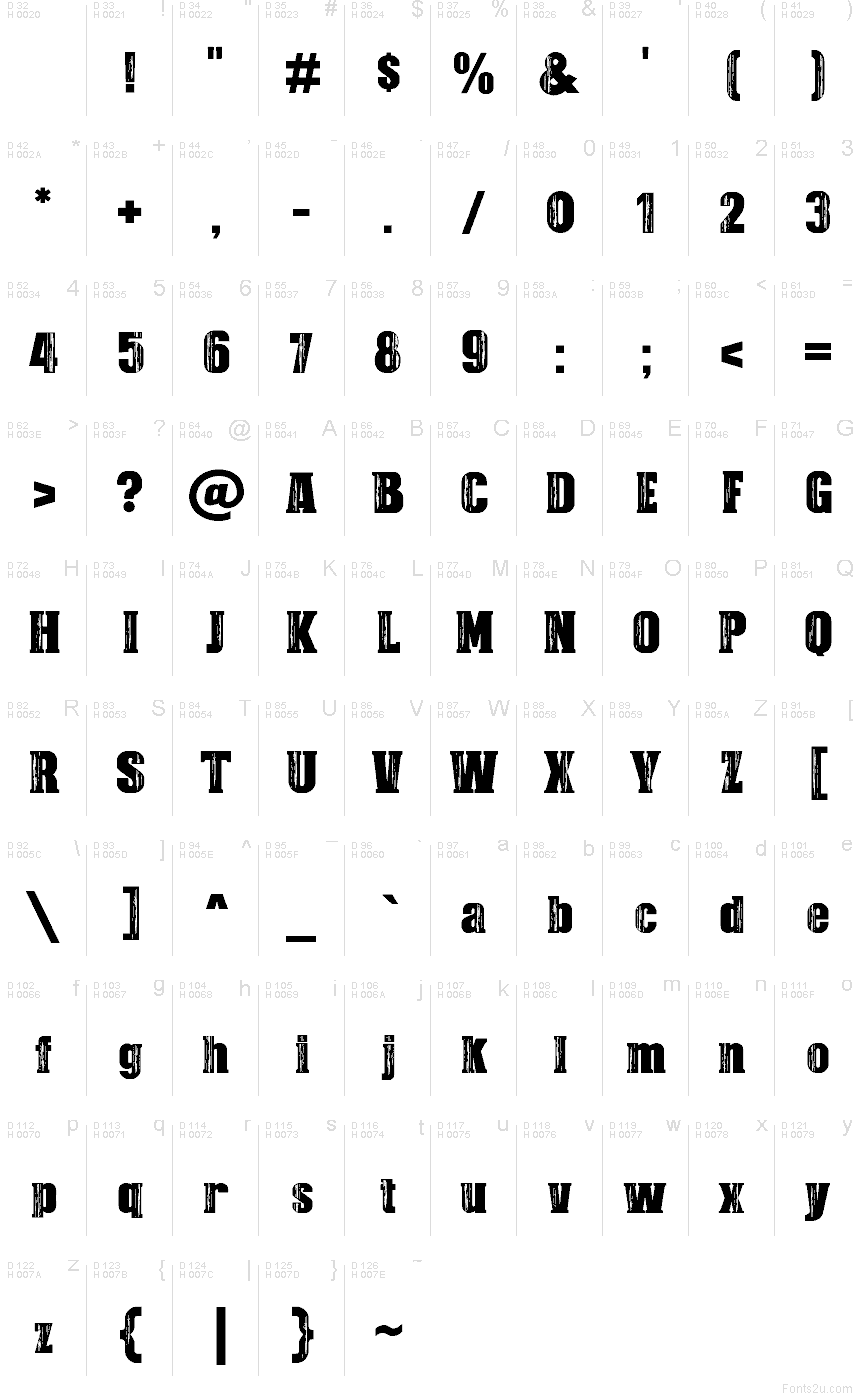
Damaged Serif, creata da Galdino Otten di Galdino Otten Fonts, è un font serif gratuito dal look distorto, che sembra quasi inchiostro trascinato su carta ruvida e lasciato asciugare a strisce. I serif audaci e squadrati rimangono leggibili, ma le imperfezioni e l'usura aggiungono una grinta immediata, come un titolo stampato con una vecchia pressa. È d'impatto senza risultare confusa, garantendo che il tuo messaggio arrivi forte e chiaro.
Damaged Serif è ideale per poster rock, titoli horror, fanzine punk, copertine di album, grafiche streetwear, schermate di avvio di videogiochi e loghi dal sapore vissuto. Usa Damaged Serif in dimensioni grandi affinché la texture sia ben visibile e abbinala a un font sans serif pulito (magari geometrico) per il testo di supporto, in modo da non creare disturbo visivo. Questo font gratuito rende al meglio anche con una spaziatura leggermente aumentata, se vuoi far respirare la texture.